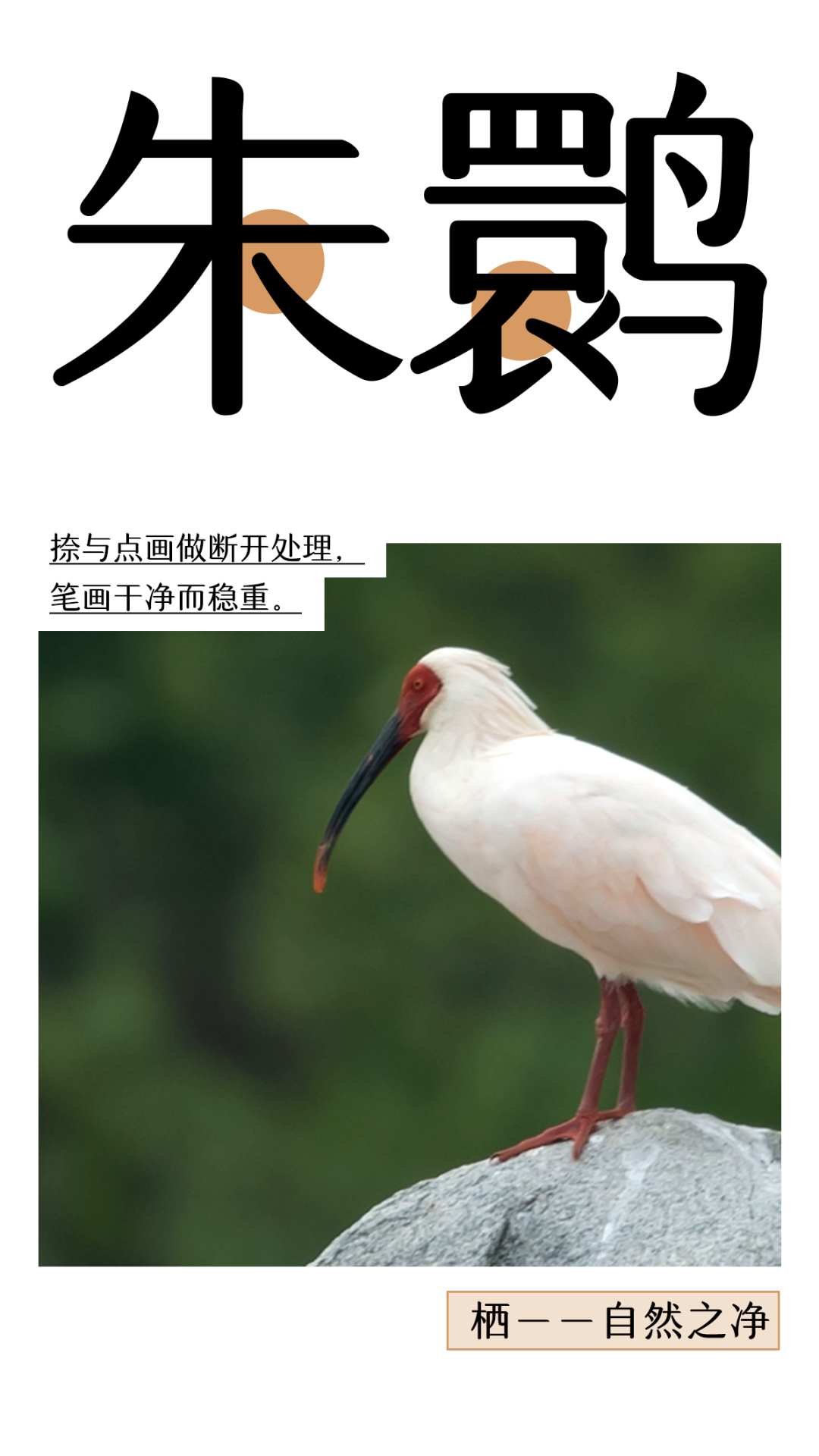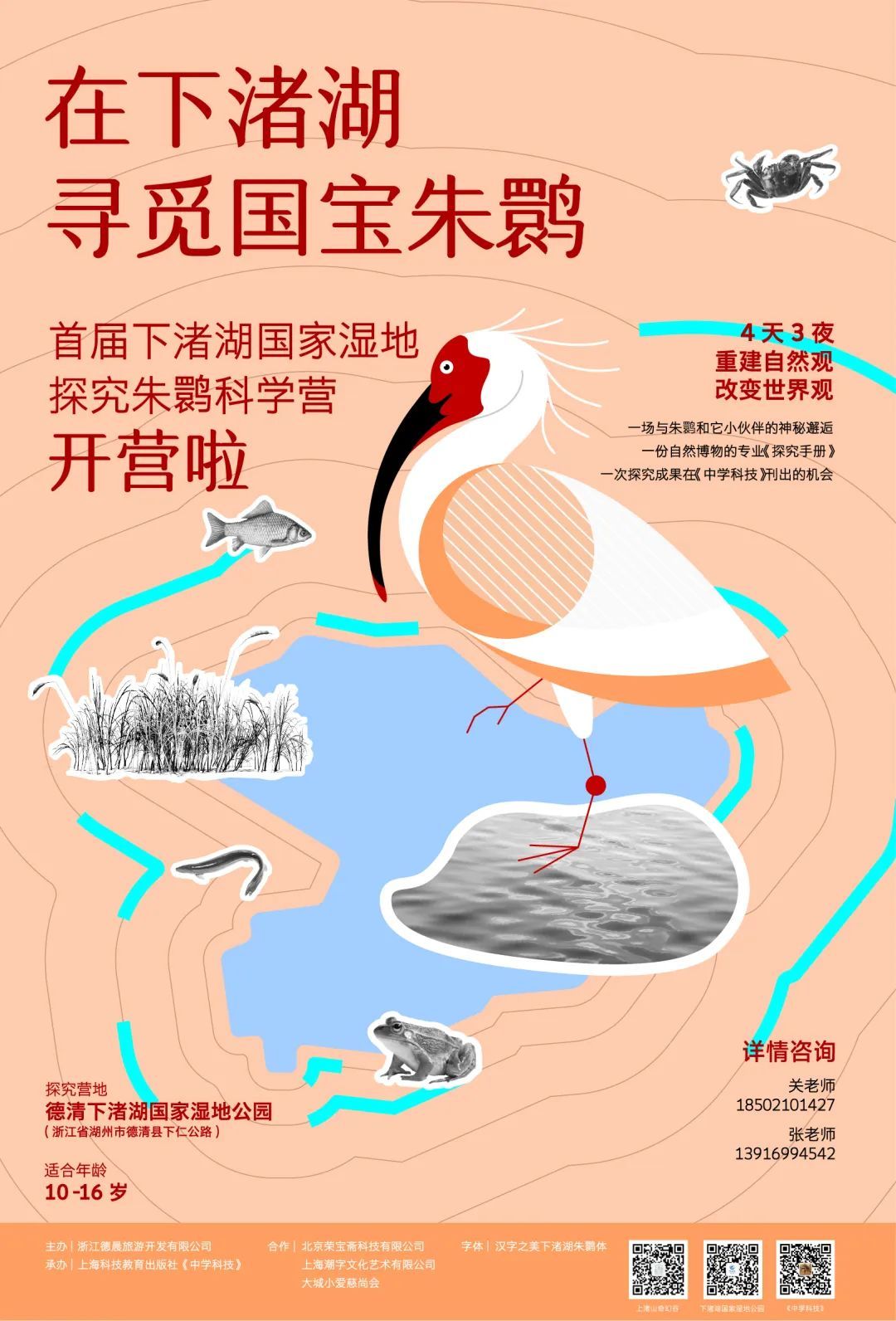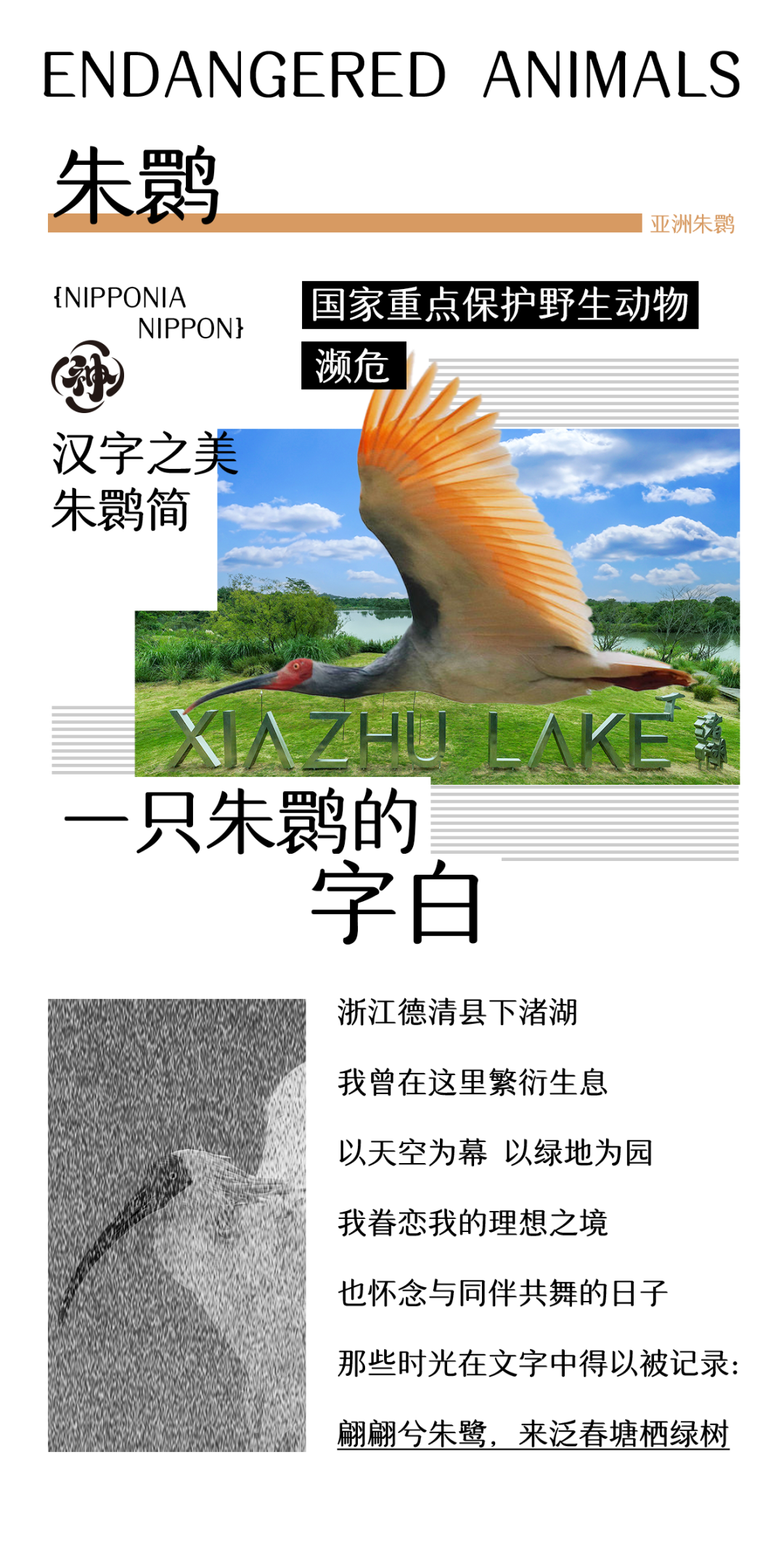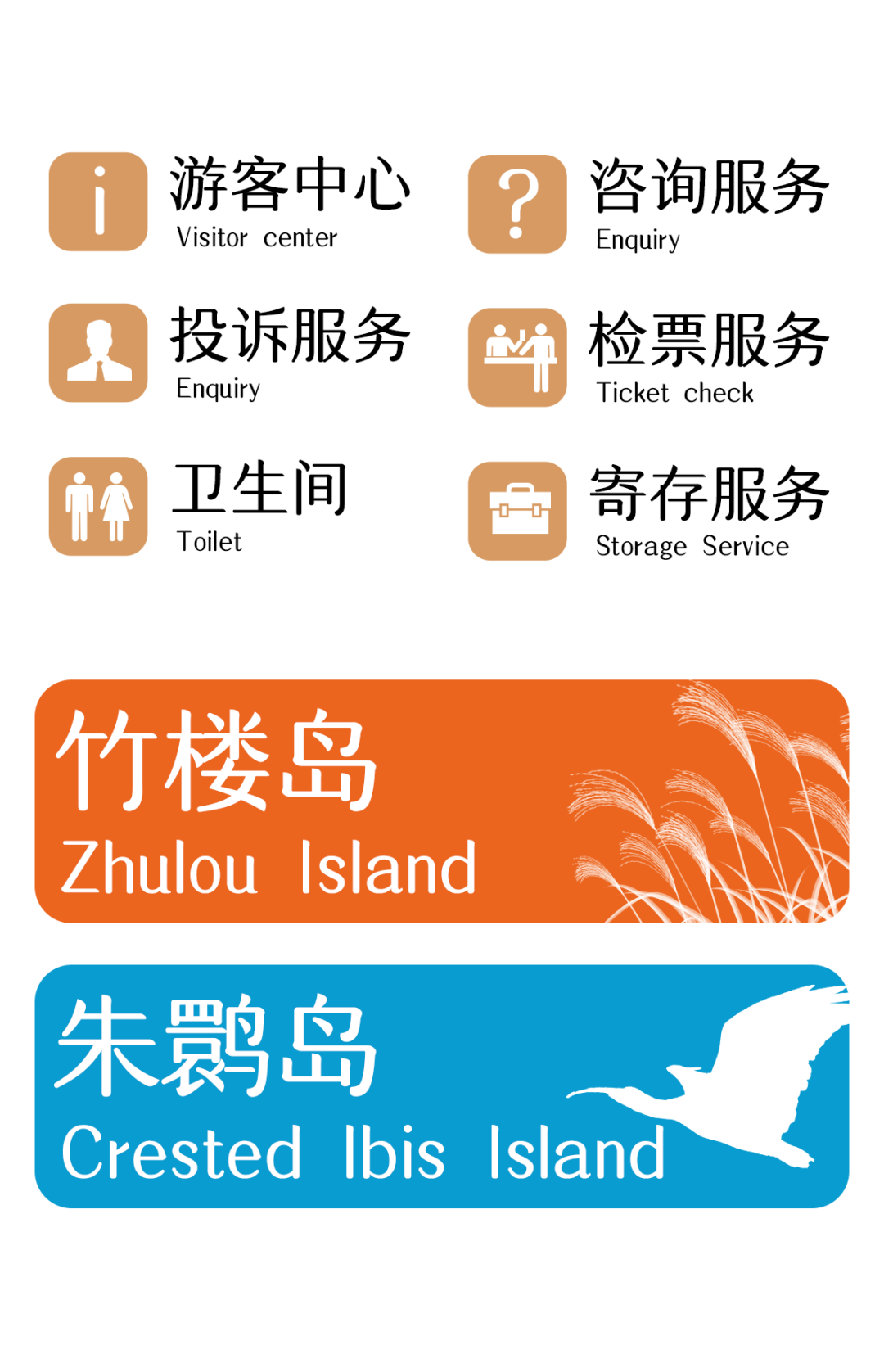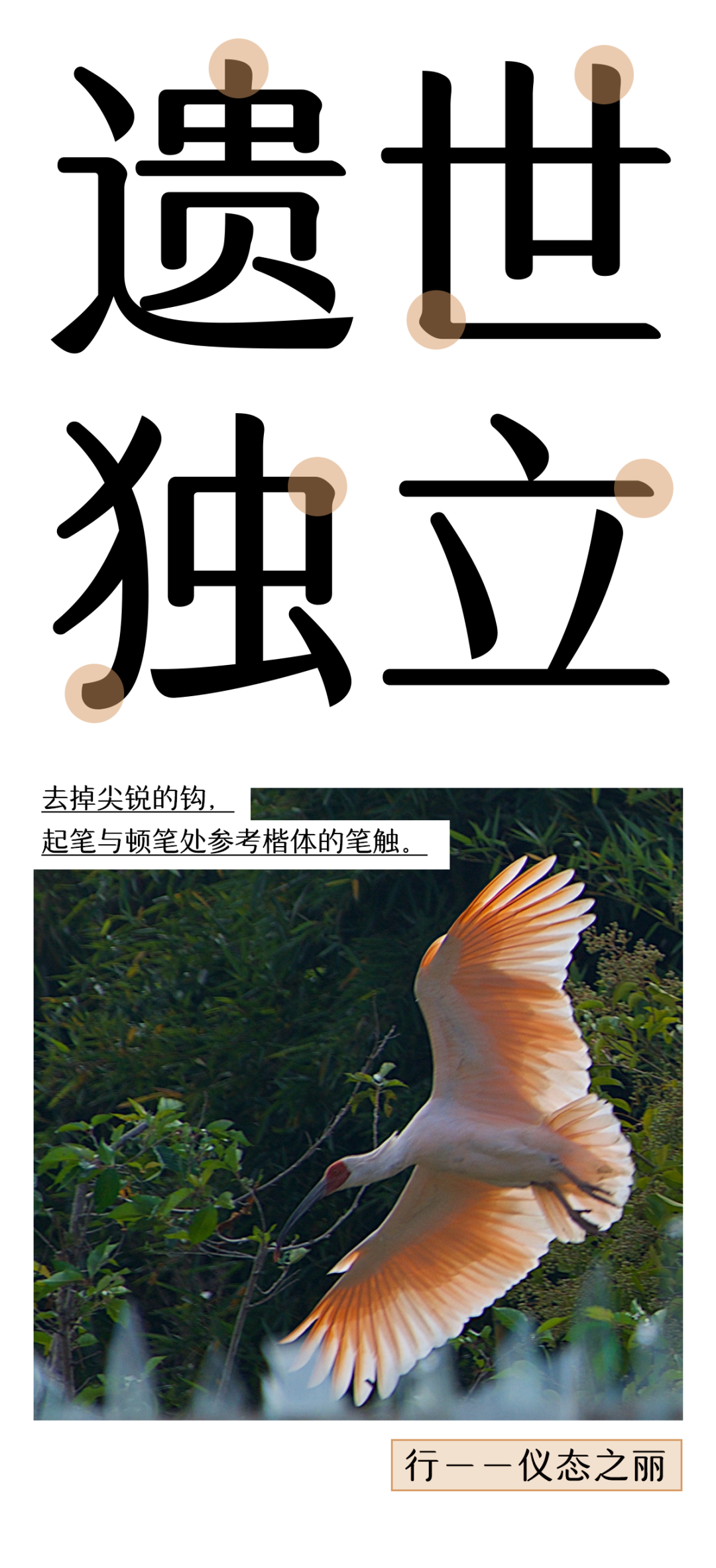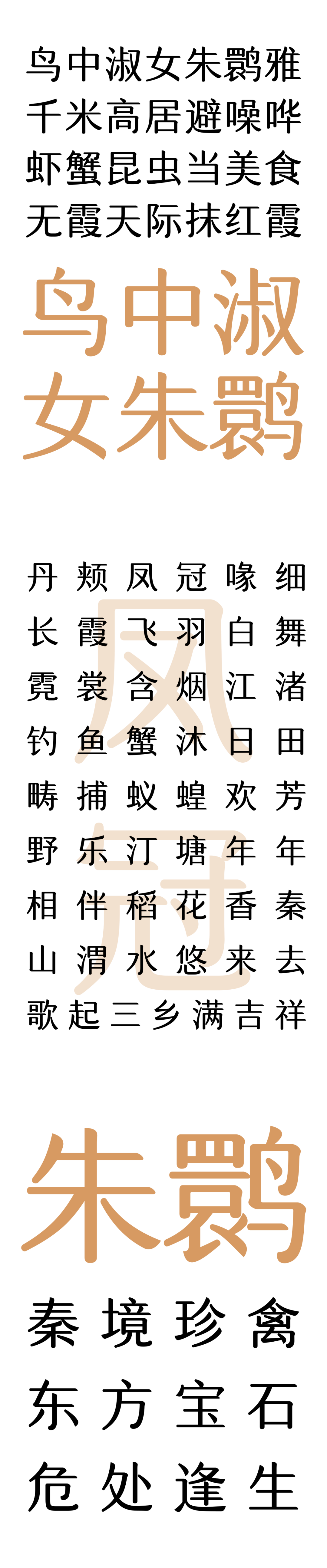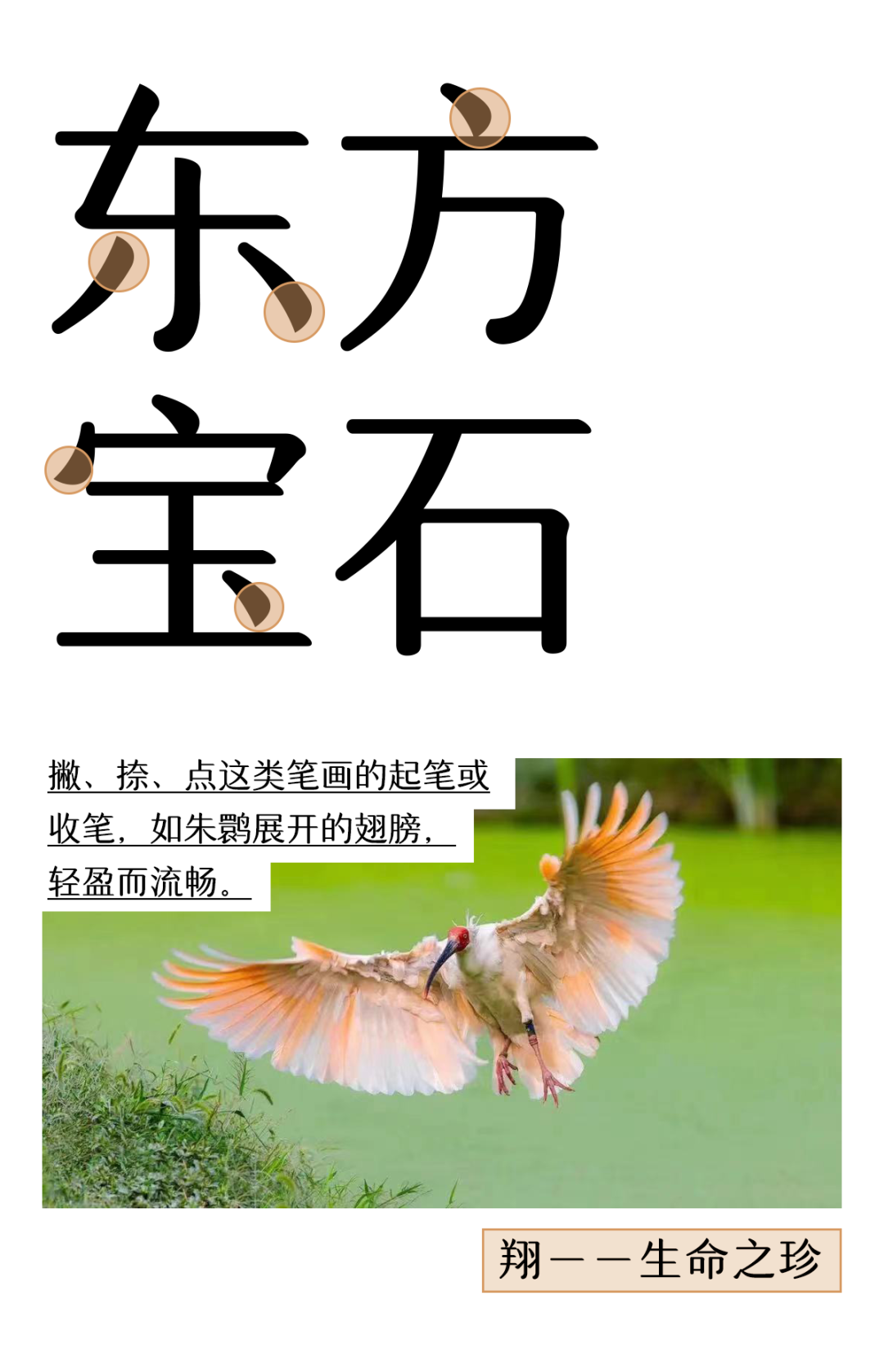
「鹮(huán)给字然」计划|字神国风x下渚湖国家湿地公园,推出联名字库“汉字之美朱鹮简”
东方宝石、鸟中大熊猫、活化石、吉祥的象征……这些美妙的雅称,都在描述这曾濒临灭绝的稀世珍禽——朱鹮(huán)。
朱鹮在被发现时,我国仅存7只。
作为朱鹮曾经的栖息地,为让其重新安家落户,2008年,在浙江省林业局的帮助下,德清县最先开始向国家申请建设德清县朱鹮抢救保护基地,这里也成为朱鹮易地保护暨浙江种群重建基地。
在多方共同努力下,德清朱鹮种群已成为全国第三大朱鹮种群,德清朱鹮繁育基地也成为全国最大朱鹮人工繁育种源基地。
史料中“翩翩兮朱鹮,来泛春塘栖绿树”的记录,用文字打开了我们对于朱鹮的美妙想象。而如今,我们也可以用汉字,将守护朱鹮的愿望,散播至各地。
万物有灵,万字有意。字神国风书法字体x下渚湖国家湿地公园,联合发起「鹮给字然」计划,共同推出联名字库「汉字之美朱鹮简」字体,传递保护珍稀鸟类、呼吁人与自然和谐相处的理念,寓情于字,让朱鹮回归“字”然。
汉字之美朱鹮简,以朱鹮“翔”“行” “栖”三种姿态为设计灵感:
撇、捺、点这类笔画的起笔或收笔,调整为如鸟类展翅的外轮廓的形状,笔画构造模拟飞翔的姿态,展现出朱鹮的轻盈、自由,流畅而富有韵律感。
为了与朱鹮的矜持、优雅相契合,去掉尖锐的钩,其他笔画的起笔与顿笔处参考楷体的笔触。字体透露着华丽、优雅的姿态,让人们在阅读的同时感受到朱鹮的娴雅高洁与绰约多姿。
从朱鹮静栖的形态中提炼笔画,捺与点画在加粗的同时做断开处理、整体结构有宋的面貌。不做过多的修饰,字体的结构不做太多变化,笔画设计尽可能纯粹,干净而稳重。
下渚湖国家湿地公园,位于浙江德清县城东南,这里港叉交错,芦苇成片,湖水清澈,野鸟群息,水生动植物遍布,仍保持了自然质朴、原始野逸的江南水乡风貌,曾获“中国最美湿地”荣誉称号。
这里是鸟类的天堂,栖居着大量野生珍稀鸟禽,更是鸟类“大熊猫”——朱鹮易地保护暨浙江种群重建基地。德清引进朱鹮后,实施朱鹮人工迁地保护和野外种群重建工程,恢复湿地生态系统,打造水清、岸绿、景美的栖息地,在下渚湖国家湿地公园建立朱鹮人工繁育种群。
这项朱鹮动物保护联名字体活动,不仅仅作为一个字体设计项目,更是对于自然生命的赞美与敬畏。我们希望这款字体能够在日常生活中广泛应用,通过字体的审美形式,引导更多人参与到朱鹮保护队伍中来,传递对朱鹮这一美丽生物的珍视与关怀,引发大众思索人与自然的关系。
目前,汉字之美朱鹮简已逐步被推广应用:
首届下渚湖国家湿地
探究朱鹮科学营即将开营
朱鹮体助力媒体宣传
汉字之美朱鹮简
类型:创意字体
风格气质:国风、简约、经典
字体设计师:钱浩
字符数:8989